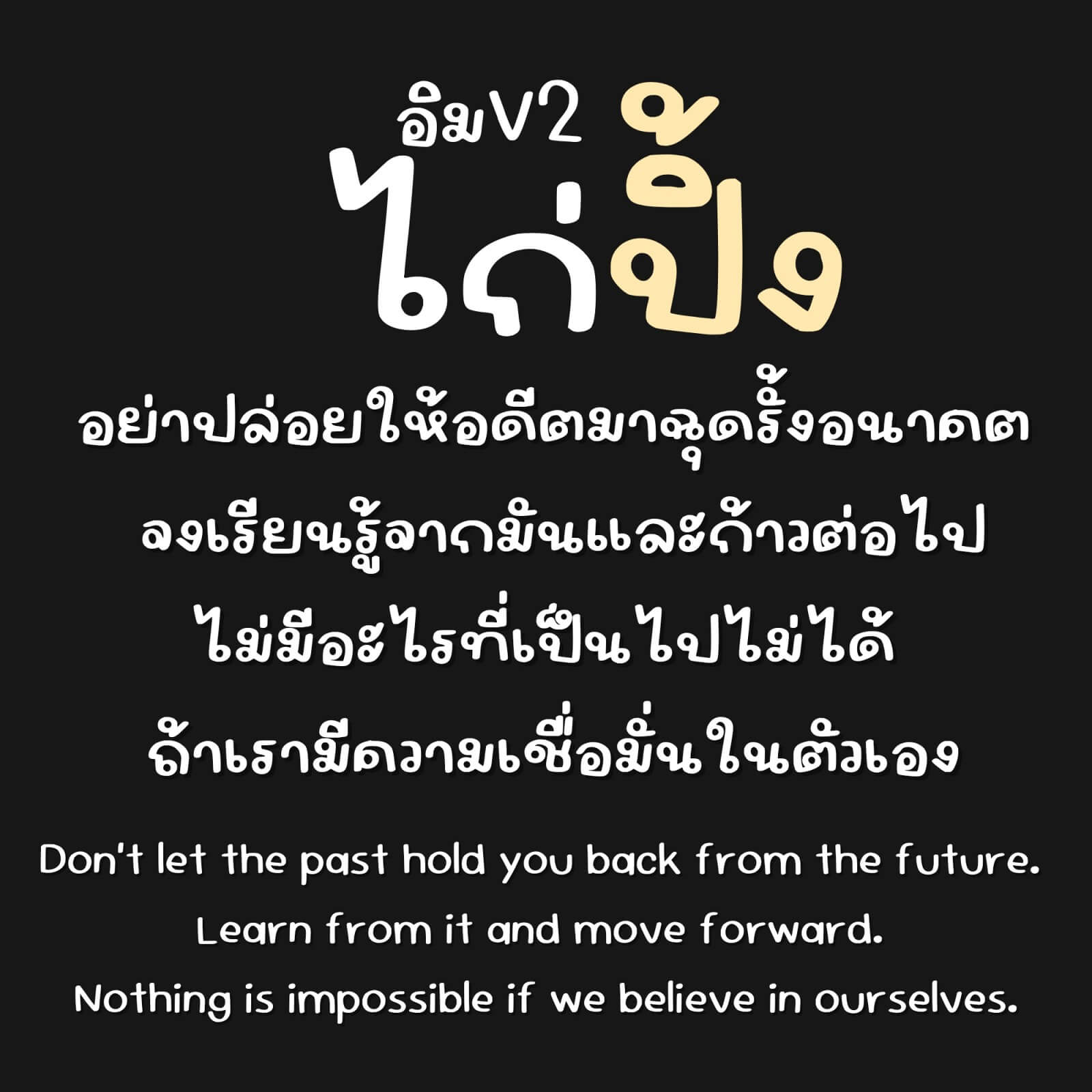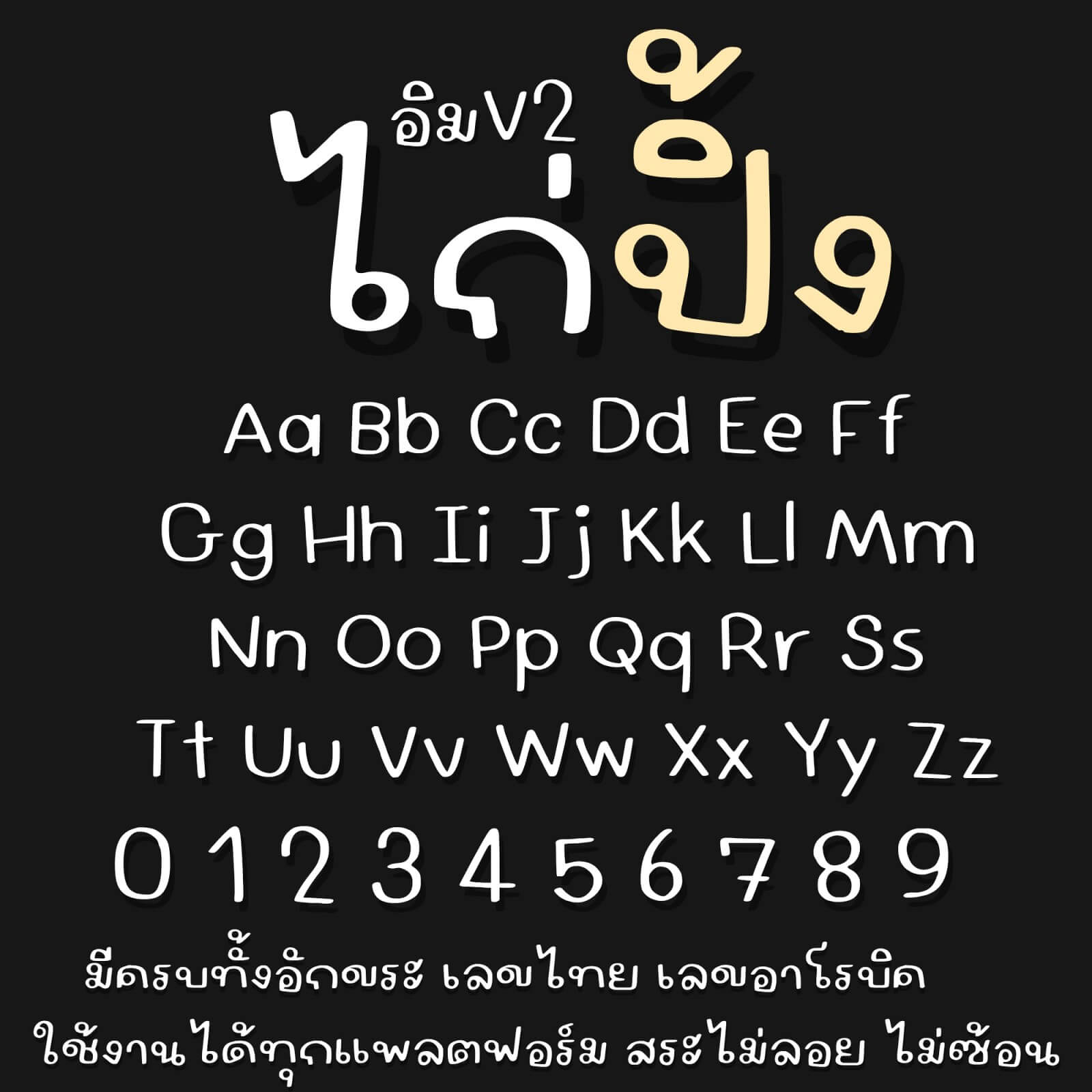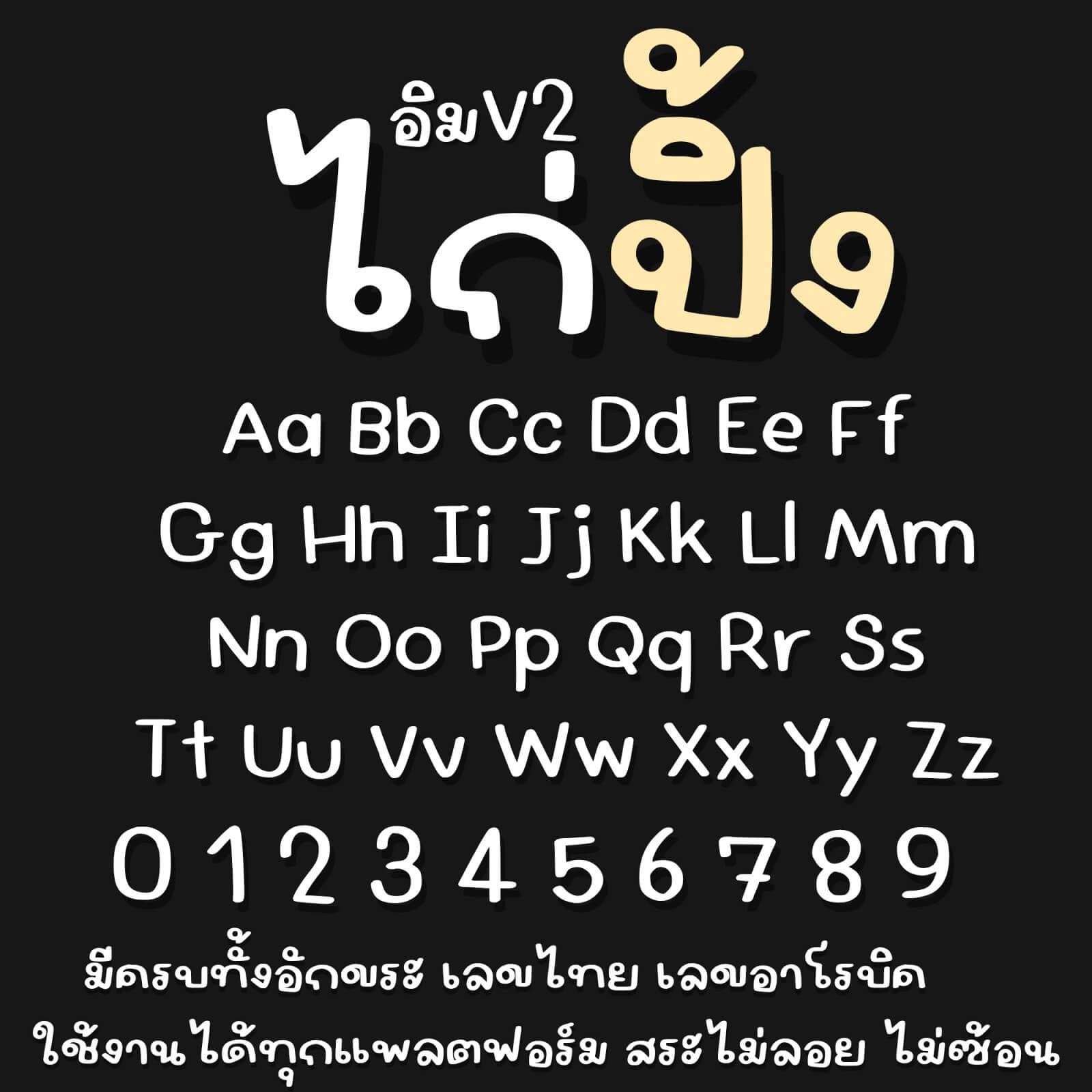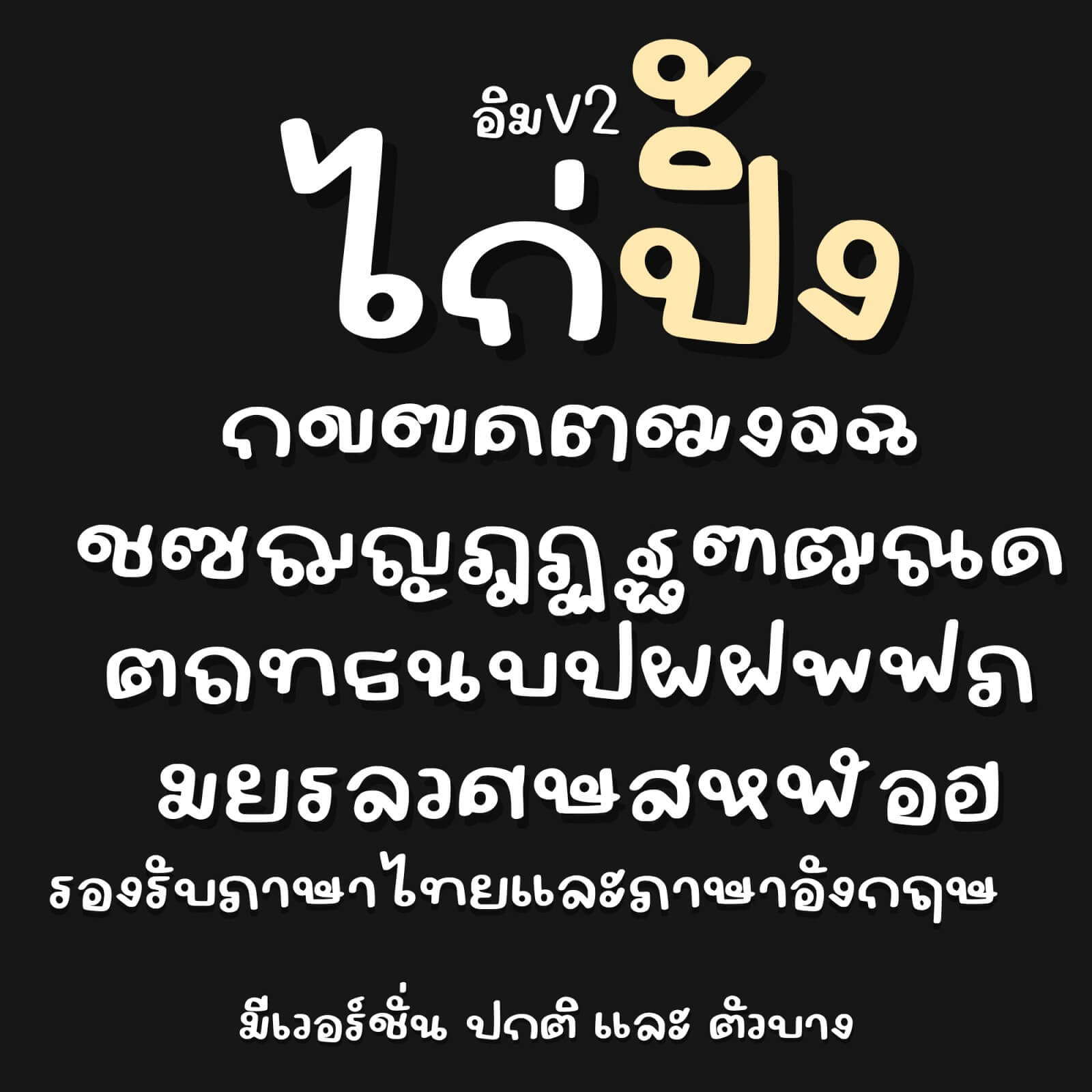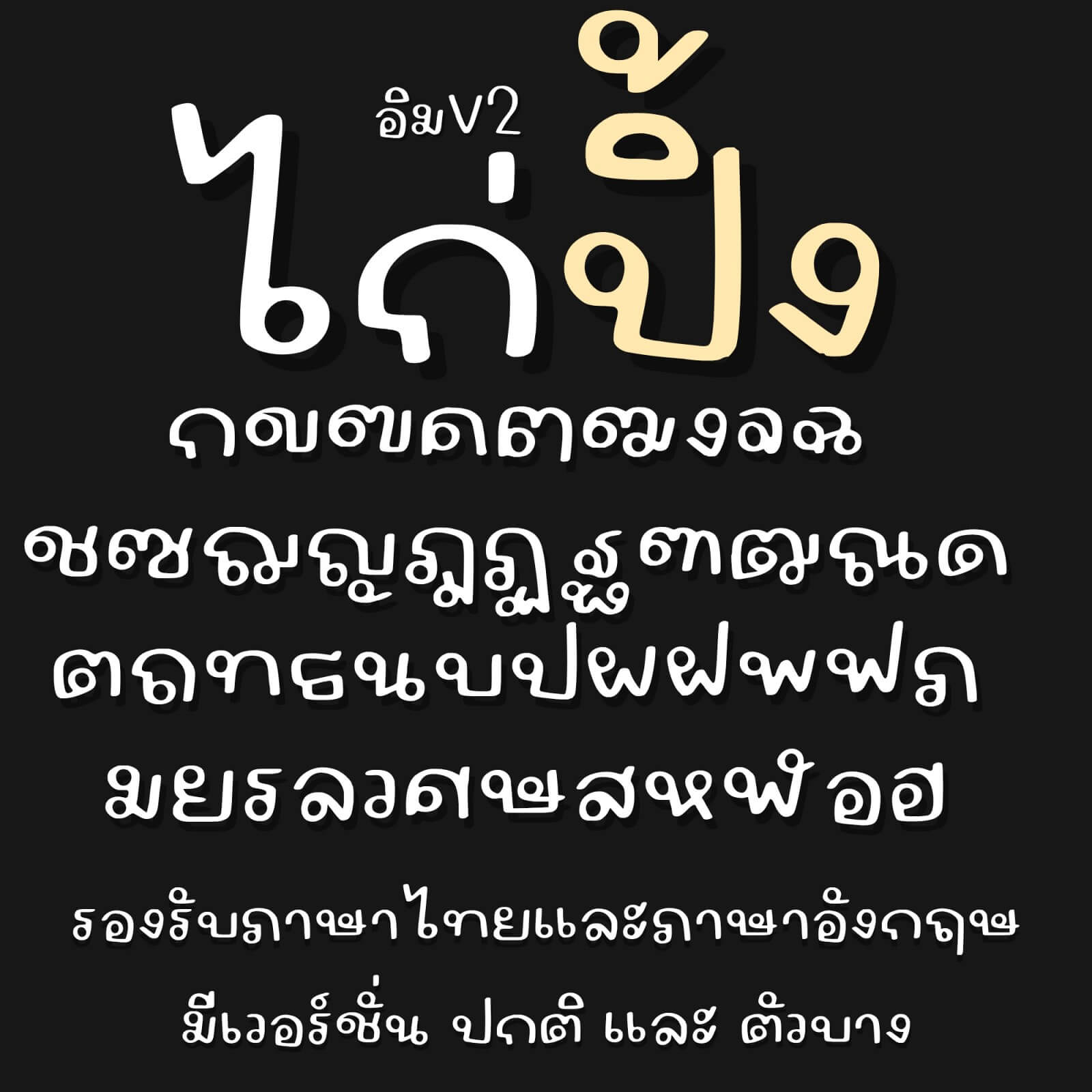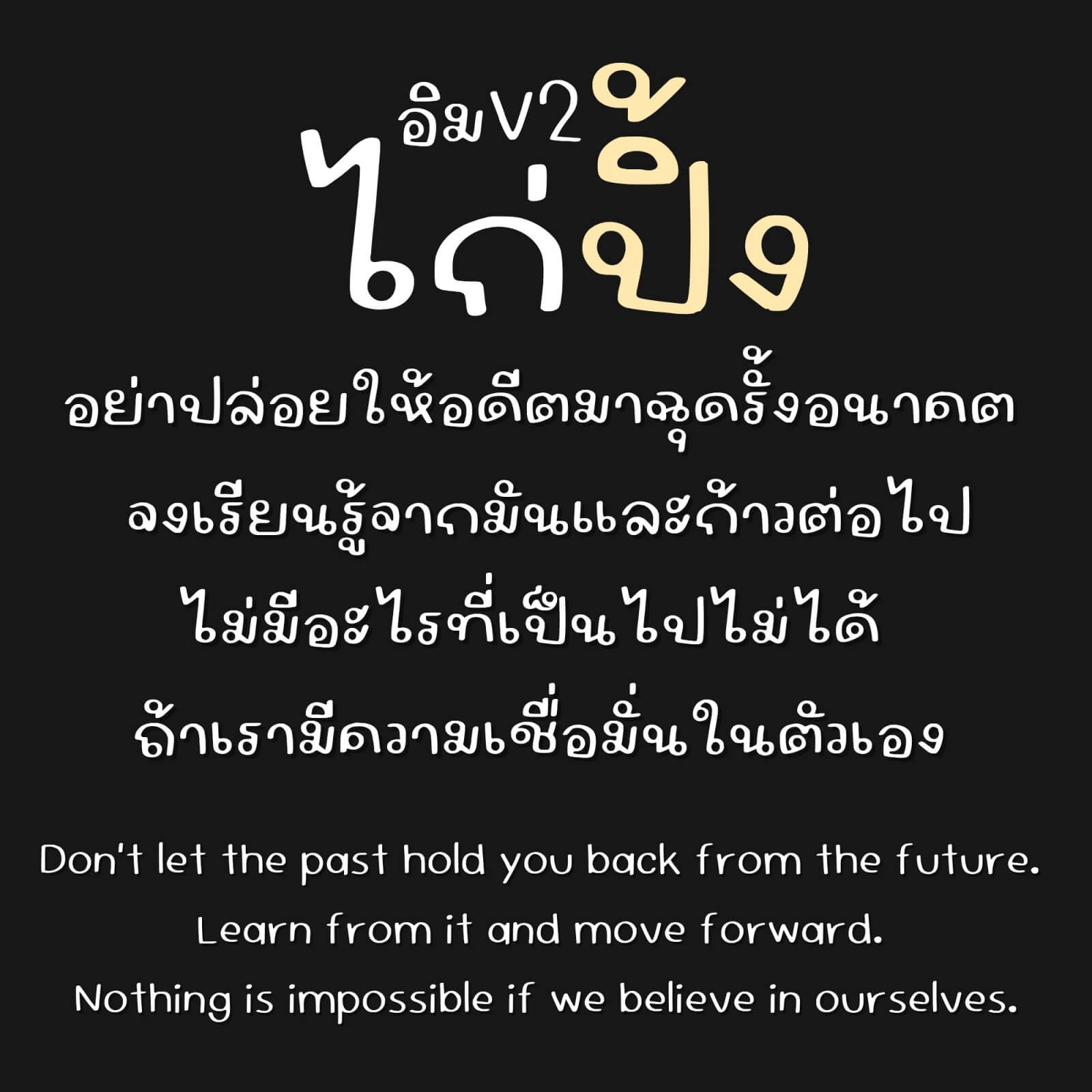
แจกฟรีตัวเต็ม!! IMTYC ไก่ปิ้ง – ฟอนต์เส้นหนามีบางเท็กซ์เจอร์เหมือนเขียนด้วยบรัชแบนนิดๆ ตัวอ้วน แฟนซี อ่านง่าย ใช้แล้วน่ารักกับทุกงานเยยย
เหมาะกับทุกสายครีเอเตอร์ ไม่ว่าจะใช้ทำป้าย ข้อความ โพสต์ หรือคอนเทนต์น่ารักๆ